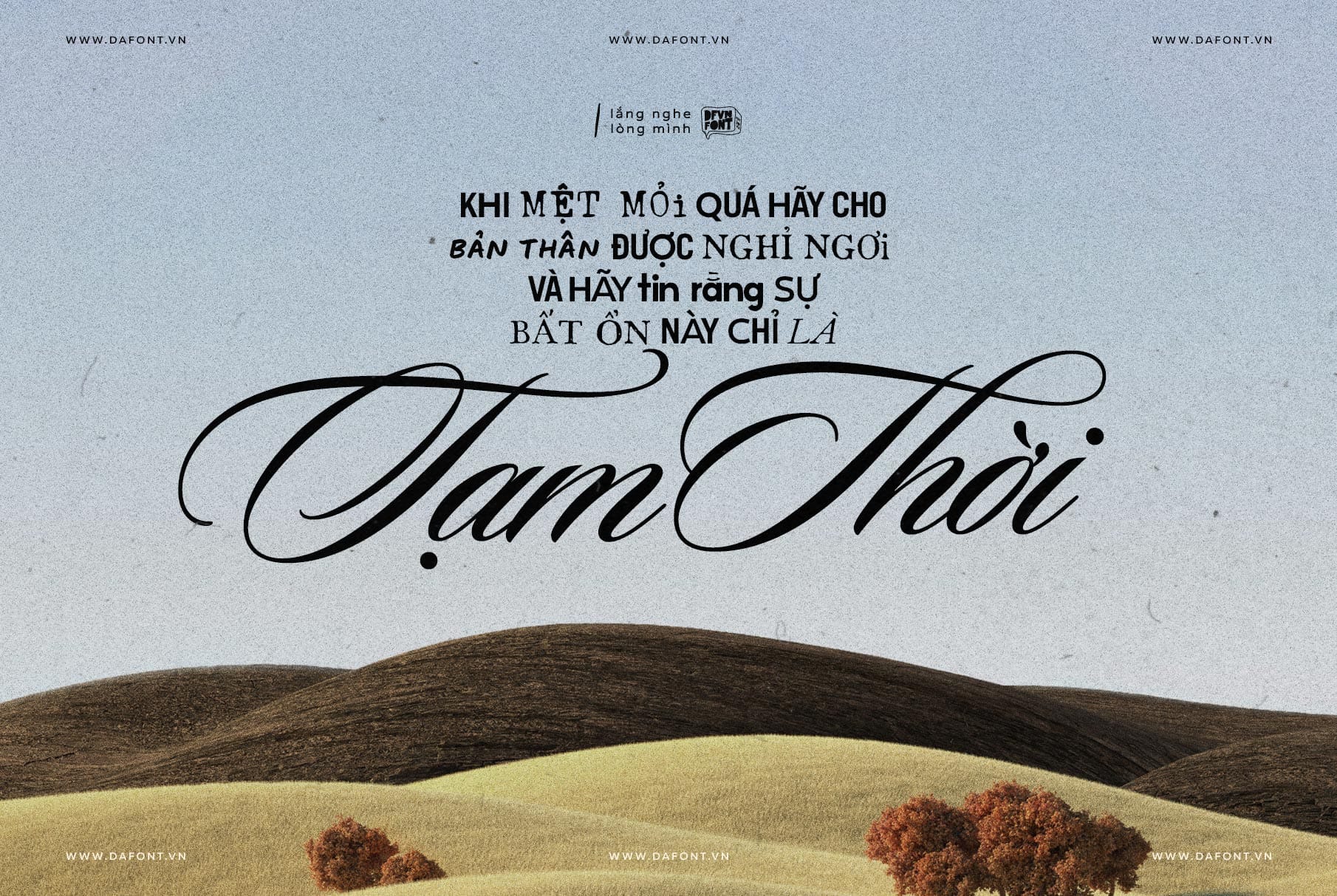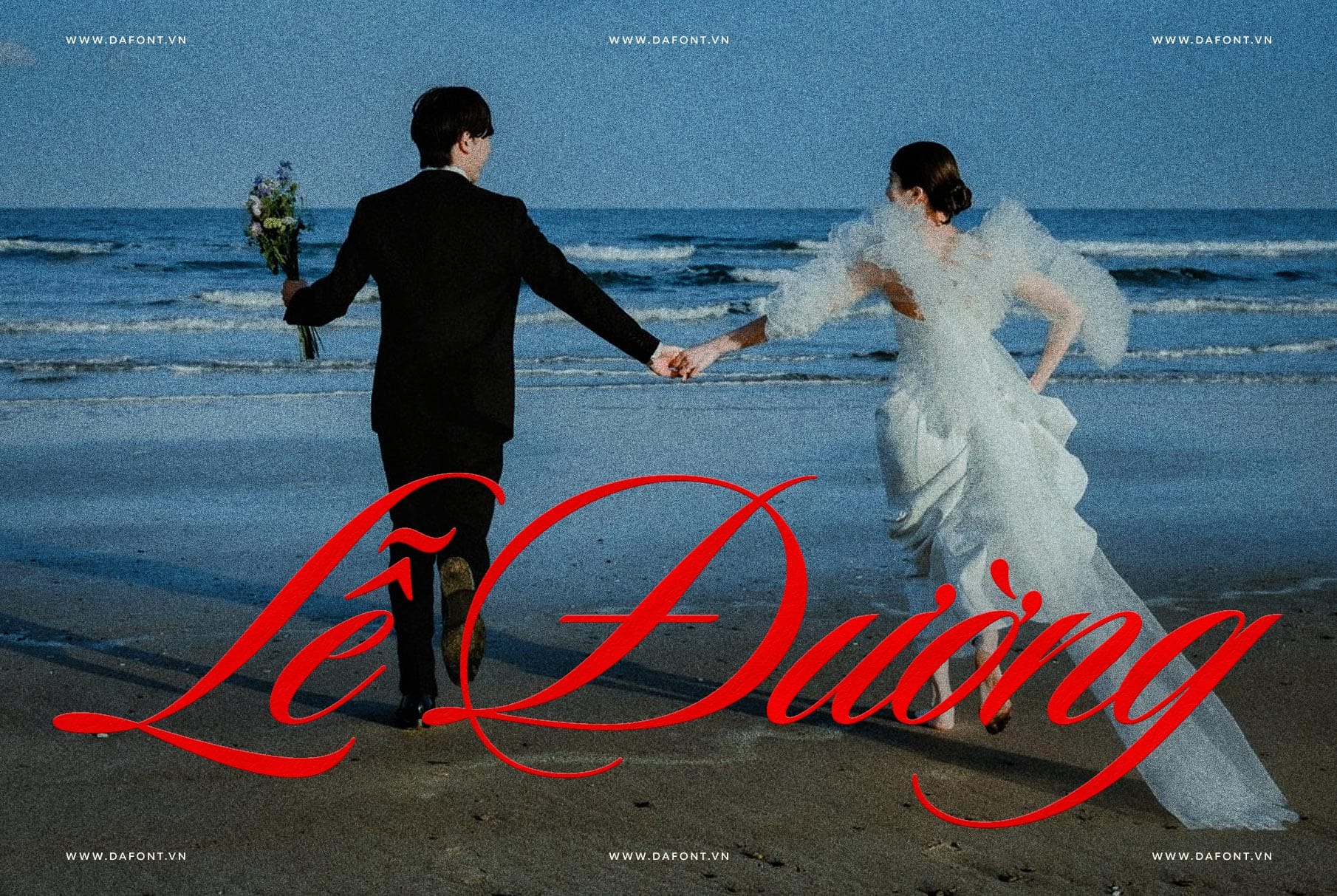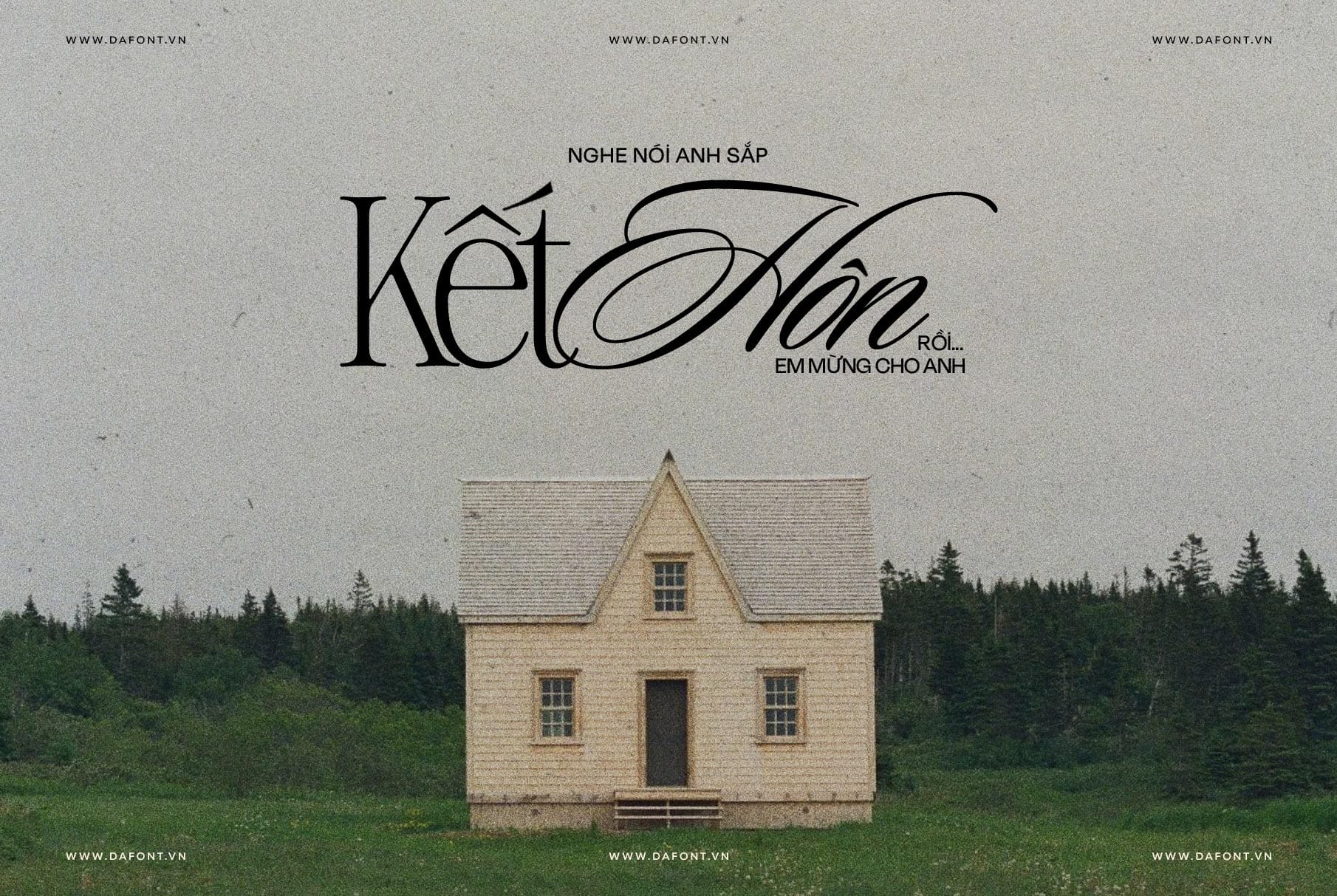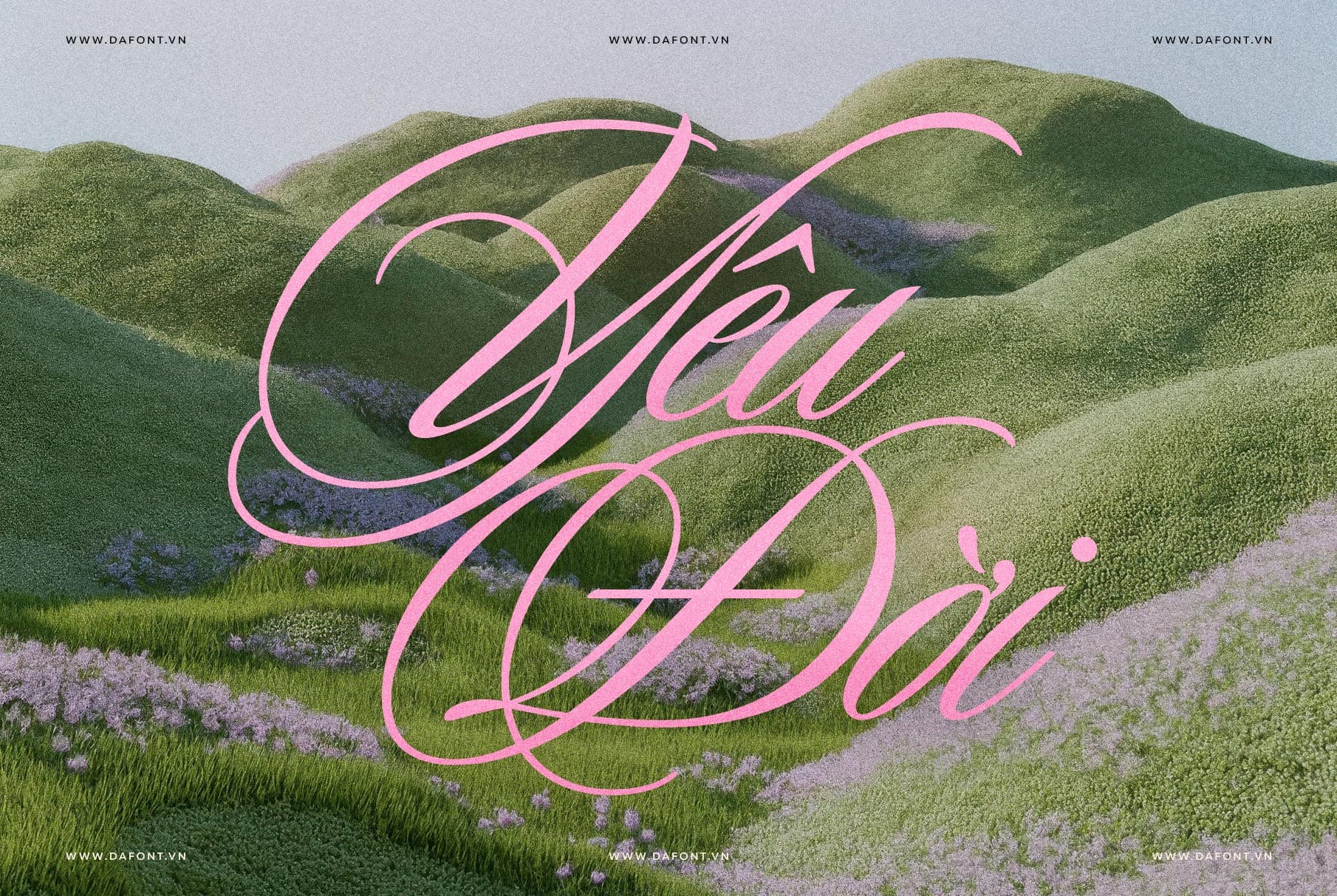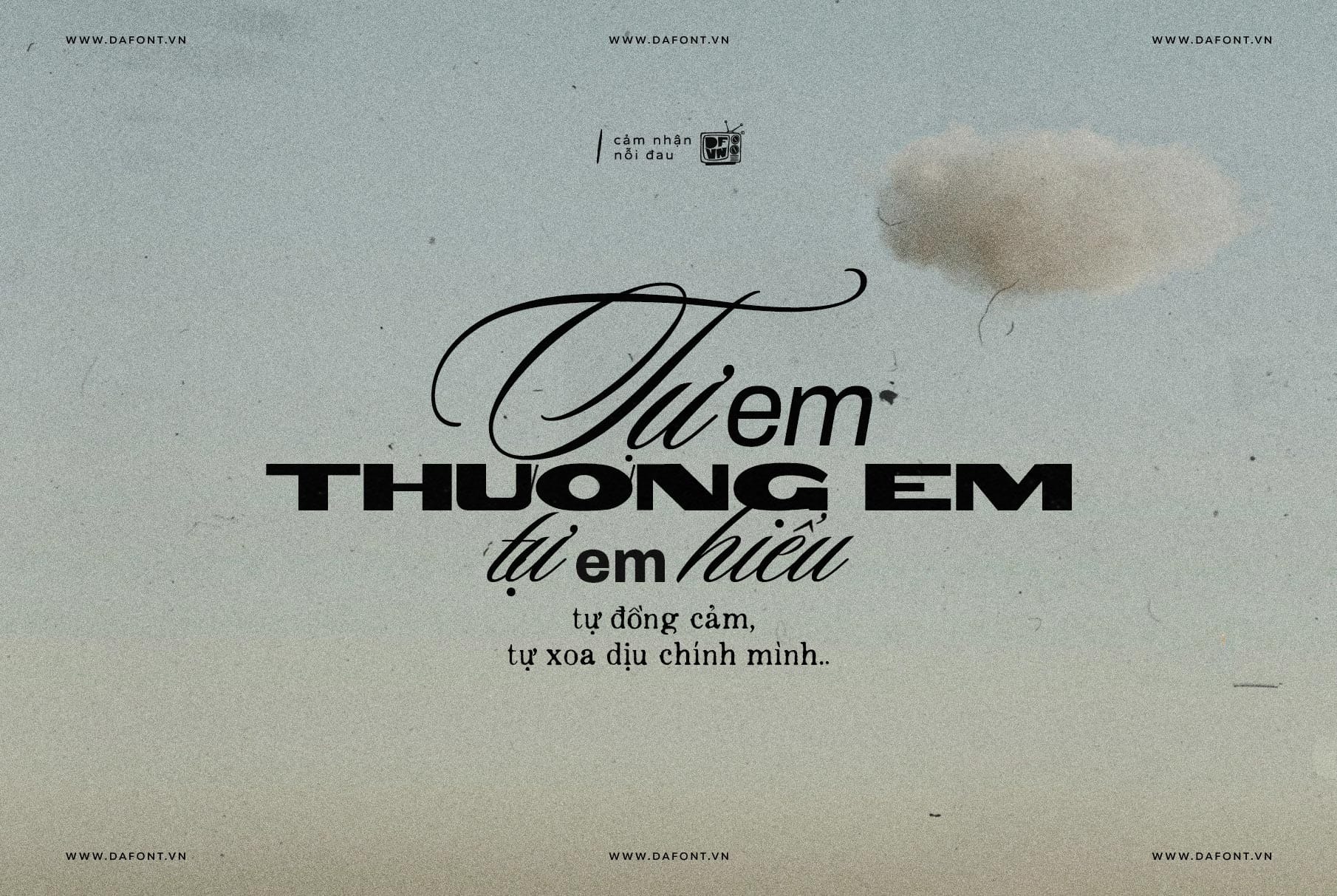
Bạn đang tìm kiếm một font chữ script mang phong cách cổ điển, thanh lịch và đầy cuốn hút? DFVN Sloop Script Pro font chính là lựa chọn hoàn hảo! Với thiết kế lấy cảm hứng từ chữ viết truyền thống, font này đã chinh phục hàng triệu nhà thiết kế trên toàn thế giới. Nếu bạn đang cần font chữ cho thiệp mời đám cưới, thiết kế thương hiệu hay đồ họa tiêu đề bắt mắt, đừng bỏ lỡ!
Giới thiệu về DFVN Sloop Script Pro
Sloop Script font được ra mắt lần đầu tiên vào năm 1994 dưới tên gọi Sloop bởi Font Bureau. Nhà thiết kế Richard Lipton – đã mang đến cho font này những nét cong mượt mà, gợi nhớ đến phong cách calligraphy cổ điển. Năm 2016, font được chuyển quyền sở hữu sang Lipton Letter Design và đổi tên thành Sloop Script. Đến năm 2018, phiên bản nâng cấp Sloop Script Pro ra đời, với hỗ trợ ngôn ngữ mở rộng và các tính năng OpenType thông minh hơn.
Năm 2018, phiên bản mở rộng Sloop Script Pro được ra mắt – tích hợp nhiều cải tiến công nghệ OpenType như những lựa chọn kiểu chữ (stylistic sets), chữ viết nhỏ (small caps), swashes, ligatures, và alternates.
Richard Lipton, người sáng lập Lipton Letter Design, đã lấy cảm hứng từ những nét bút lông truyền thống để tạo nên font chữ này. Kể từ khi ra mắt, Sloop Script đã trở thành biểu tượng trong lĩnh vực typography, thường được sử dụng trong các dự án cần sự tinh tế và sang trọng.
Đặc điểm nổi bật DFVN Sloop Script Pro
- Nét chữ thư pháp sang trọng: DFVN Sloop Script Pro được thiết kế với những đường cong mềm mại, uyển chuyển như chữ viết tay, mang lại vẻ ngoài tinh tế và đẳng cấp.
- Kerning và tối ưu dấu hoàn hảo: Toàn bộ ký tự và dấu được tinh chỉnh kỹ lưỡng, khoảng cách chữ (kerning) cân đối, đảm bảo văn bản hiển thị hài hòa, đẹp mắt và dễ đọc.
- Tính năng OpenType hiện đại: Ligatures (chữ ghép tự động), Stylistic Alternates (chữ thay thế nghệ thuật), Swashes (nét kéo bay bổng đầu/cuối chữ), Contextual Alternates (chữ biến đổi theo ngữ cảnh). Những tính năng này cho phép bạn sáng tạo vô tận, tạo ra nhiều phong cách độc đáo.
- Nhiều phiên bản & độ dày chữ: Bao gồm 3 kiểu Regular, Medium, Bold và phiên bản Pro với hơn 1.450 glyph đều được Việt hóa tỉ mỉ và cẩn thận, giúp bạn linh hoạt trong nhiều thiết kế khác nhau.
- Ứng dụng đa dạng: Hoàn hảo cho logo thương hiệu, thiệp cưới, bao bì sản phẩm, tiêu đề poster, bìa sách và các thiết kế cao cấp khác.
DFVN Sloop Script Pro – Nét chữ của sự sang trọng
DFVN Sloop Script Pro không chỉ đơn thuần là một phông chữ mà còn là biểu tượng của sự sang trọng, tinh tế và nghệ thuật. Với đường nét thư pháp sang trọng và mềm mại, phiên bản Việt hóa chất lượng cùng các tính năng OpenType hiện đại, Sloop Script mang đến cho nhà thiết kế một công cụ mạnh mẽ để tạo nên những tác phẩm đẳng cấp. Dù bạn sử dụng cho logo thương hiệu, thiệp cưới, bao bì sản phẩm hay ấn phẩm truyền thông, font chữ này luôn đảm bảo sự nổi bật và khác biệt.
Nếu bạn đang tìm kiếm một font chữ vừa đẹp, vừa chuyên nghiệp và phù hợp cho các dự án cao cấp, thì DFVN Sloop Script Pro chính là lựa chọn hoàn hảo.